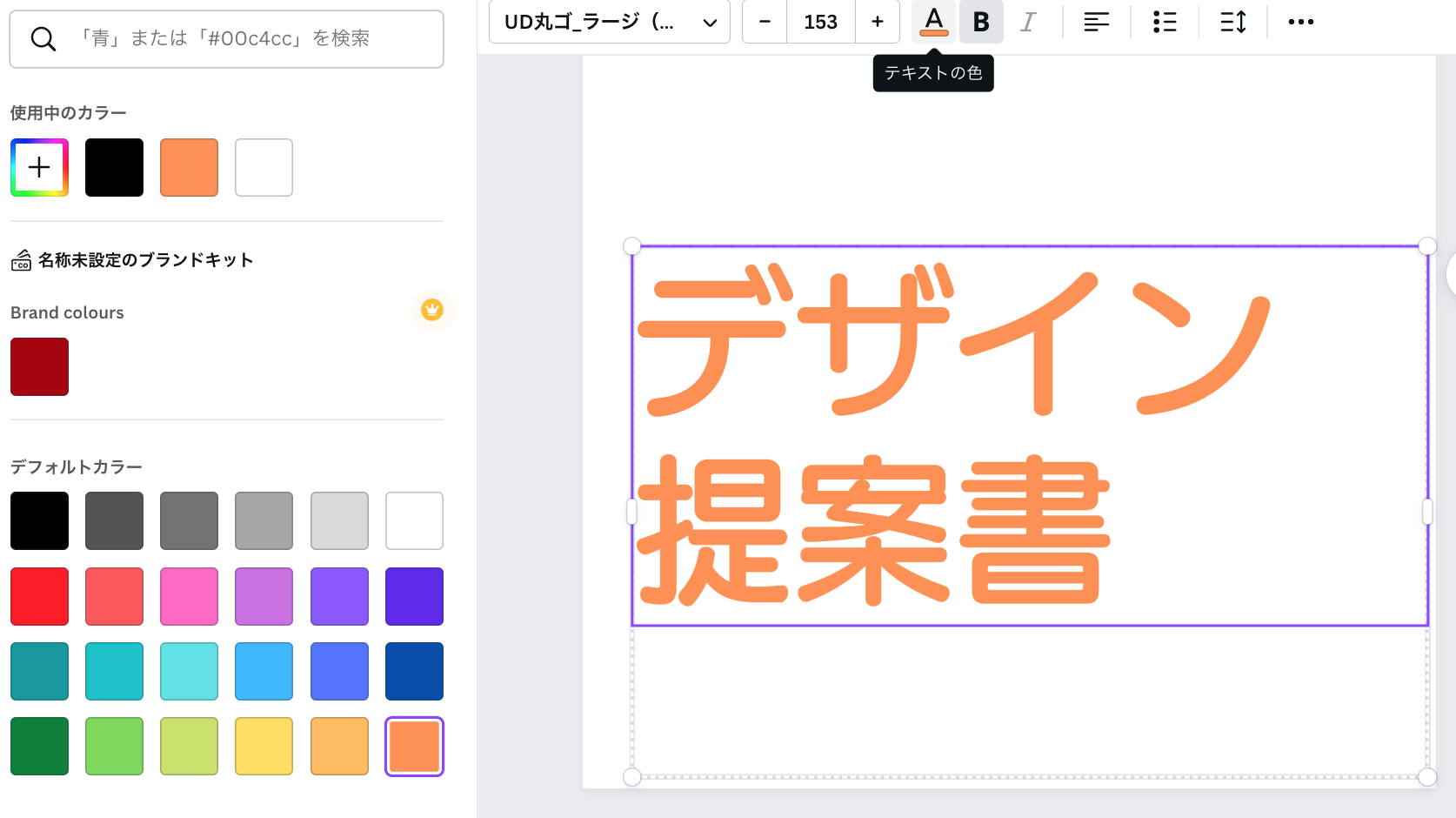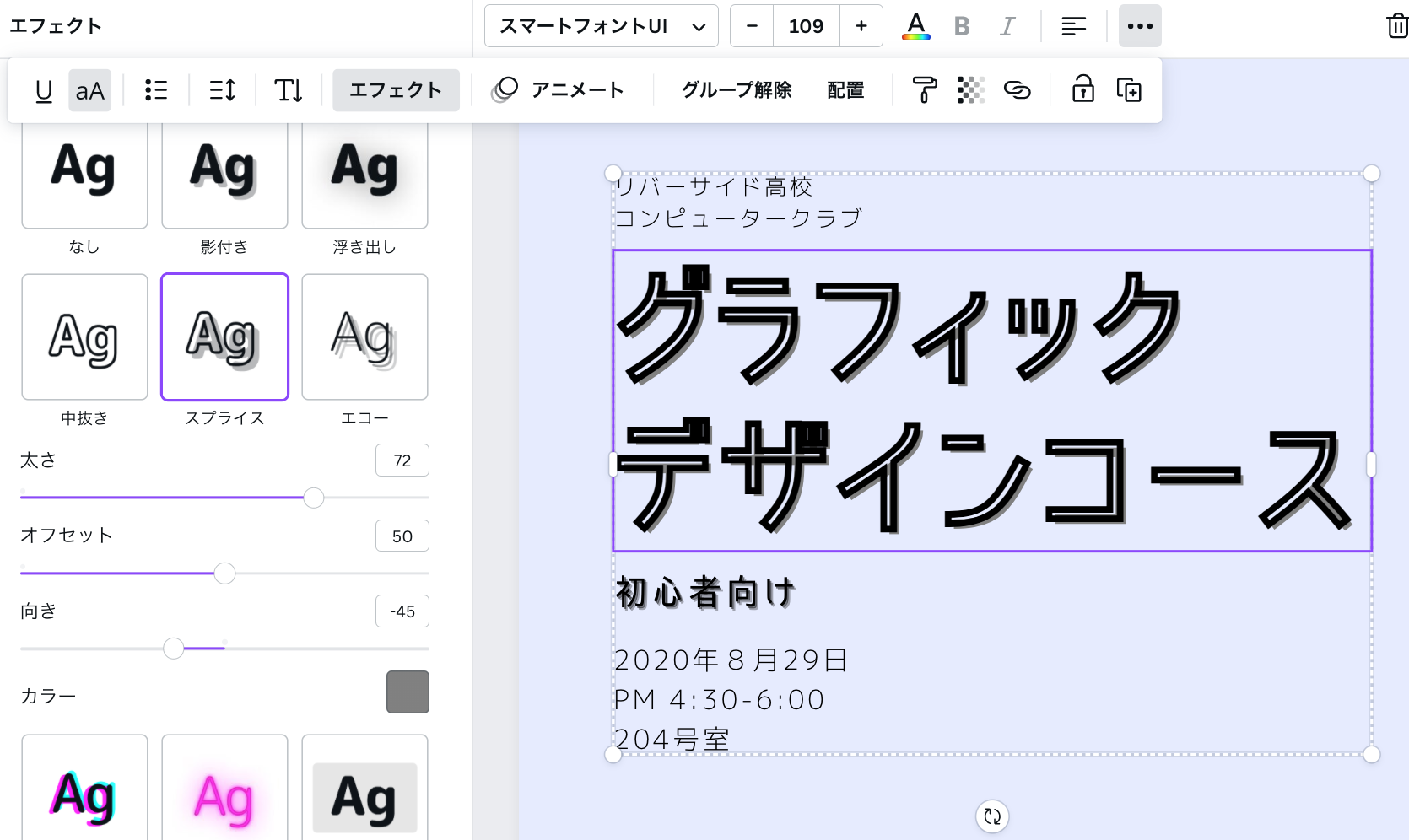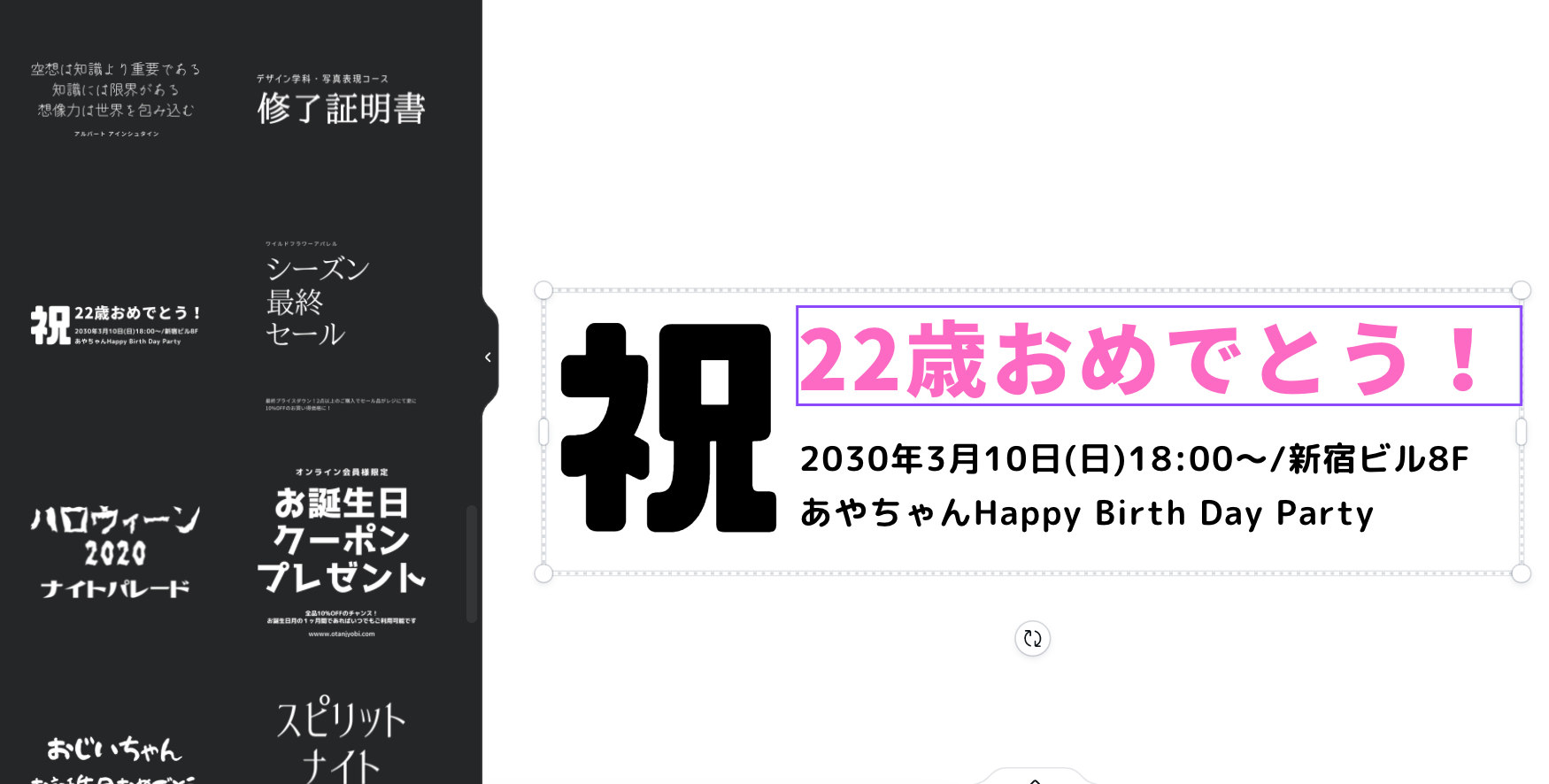
日本語フォントでデザインを作成
Canvaには日本語フォントが豊富に揃っています。
Canvaの多種多様な日本語フォントでデザインを作成する
Canvaには、何百種類もの日本語フォントがご用意されています。多種多様なフォントがあるので、派手なものからシンプルなものまで揃っています。ポップなフォント、丸みのあるフォント、手書き風のフォント、和風な筆フォントなど。様々なフォントを試すことができるので、デザインに適したフォントを選んでみてください。
日本語フォントの色、サイズを変更する方法
日本語フォントを選択し、文字を入力した後は、編集に取り掛かります。テキストの色も、もちろん編集できます。上部メニューから[A]のアイコンを押します。左画面にカラーパレットが表示されます。デフォルトカラーのほかに、「写真の色」が自動的にまとめられている機能もあります。おすすめ色を推奨してくれるので、迷わずにデザインに合ったものを選べます!サイズの変更も1単位から変更できます。
フォントの組み合わせを使って、おしゃれなデザインに仕上げよう
Canvaには、とっても便利な[フォントの組み合わせ]機能があります!テキスト画面で「日本語」と検索し、フォントを下の方までスクロールします。そうすると、数種類のフォントで組み合わされたテキストのテンプレートが表示されます。文字に強弱があり、改行も設定されています。このフォントスタイルに文字を追加することで、おしゃれでまとまりのあるデザインが完成します。
毛筆の日本語フォントを使って、文字を落ち着いた優しい雰囲気にする
日本語フォントで一段と美しく、和風の雰囲気を引き出したい方には、毛筆フォントがおすすめです。[テキスト]の検索バーに「筆」と入力すると、あらゆる筆フォントが表示されます。万年筆や掛け軸にあるようなフォントが見つかります。中でも「衛山毛筆」というフォントはハガキやお中元の添え状にも使える、スタイリッシュかつフォーマルなフォントです。筆フォントでメッセージに優しい雰囲気を足してみませんか?
日本語フォントに背景や影をつけて、文字を引き立たせる方法
文字を選択した後、上部のメニューバーから[エフェクト]を押します。左画面に様々なエフェクト機能が表示されます。影付きをテキストに適用すると、文字が飛び出しているように見せることができ、背景を適用すると、文字の部分にだけ背景が設定されます。好きなカラーを選択し、丸みや透明度など微調整することができます。、背景デザインに負けないように文字にインパクトをつけることができます。
日本語フォントの探し方とデザインに使用する方法
• デザイン画面で左のツールバーから[テキスト]にいくと、検索バーがありますので、こちらで「日本語フォント」と入力し、検索をします。さらに、筆、モダン、明朝、などのキーワードを入れて、絞り検索することもできます。